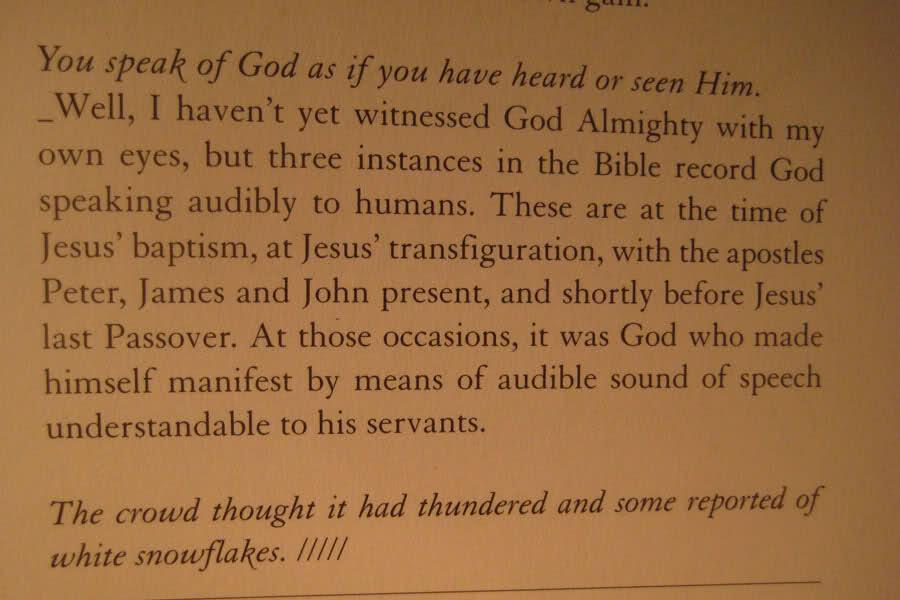
[Suche] Antiqua aus Magazin
Komm um's verrecken nicht drauf. Auch ein Blick in den Fontexplorer hat mich nicht weitergebracht. Dieses kursive »k« kenn ich definitiv. Jemand eine Idee?
das ist die granjon, würde ich sagen:
was für ein magazin ist das denn, aus dem du die zeilen abfotografiert hast?
Die Bilder sind aus einer M-Publication Ausgabe. Bin heute beim blättern über das kursive »k« gestolpert.